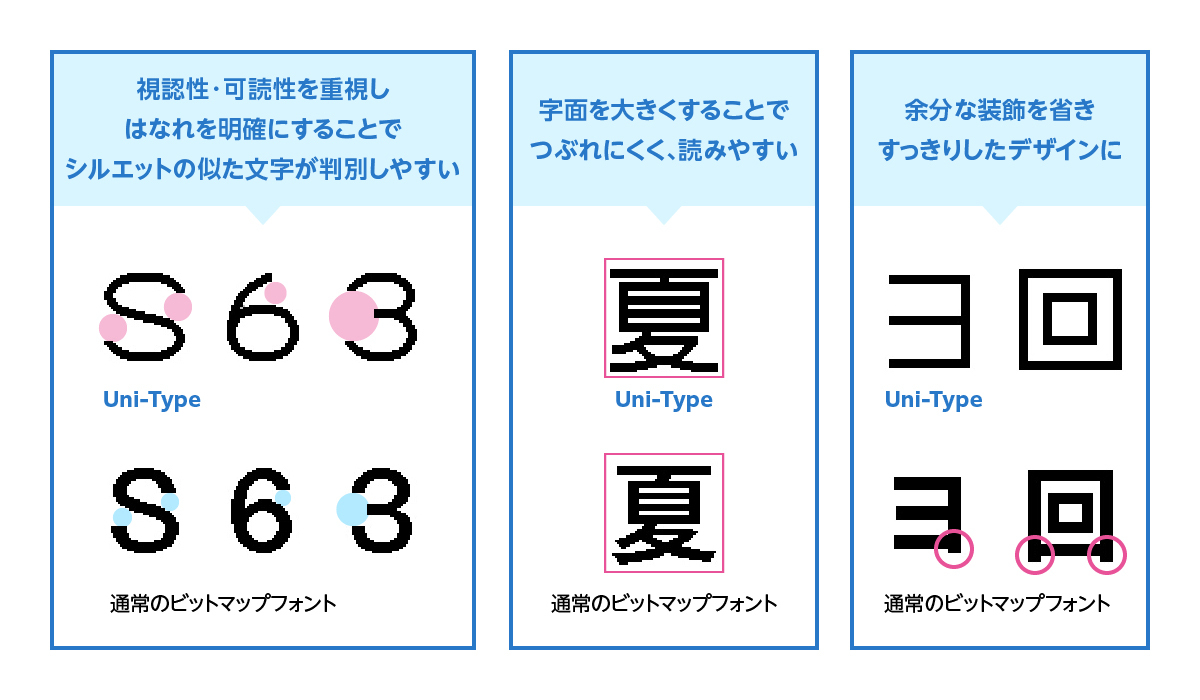
ユニバーサルデザインに対応したモリサワのビットマップフォント「Uni-Type」がキングジムのラベルライター「テプラ」新機種に搭載
モリサワはUD(ユニバーサルデザイン)に対応したビットマップフォント「Uni-Type(ユニタイプ)」がキングジムが2025年1月17日より発売予定となるラベルライター「テプラ」PRO SR-R560の搭載書体に採用されたことを2024年11月26日に発表した。
ラベルへ印字できる搭載フォントの一つとして採用された「Uni-Type」は、旧・株式会社リムコーポレーション(2022年2月モリサワに吸収合併)と、静岡県工業技術研究所との共同研究によって開発したビットマップフォントとなる。視認性・可読性を重視するUDのデザインコンセプトに基づき、シルエットの似た文字を判別しやすくしたほか、字面を大きく、装飾を省いてすっきりとしたデザインにするなど、さまざまな工夫が施されている。
「テプラ」PRO SR-R560で、このフォントを使用することにより、より多くの人にとって読みやすく、適切に情報が伝わるラベルを作成することができる。
モリサワ「UDフォント」
より多くの人に「文字のかたちがわかりやすいこと」「文章が読みやすいこと」「読み間違えにくいこと」をコンセプトに開発したフォント。モリサワでは使用目的に合わせてさまざまなフォントを取り揃えている。
メトリックスに制限のあるビットマップフォントも、UDフォントのコンセプトに基づき、点の集まりによる潰れにくさを考慮し、明るく明確なデザインにしている。第三者機関による評価や共同研究なども実施している。